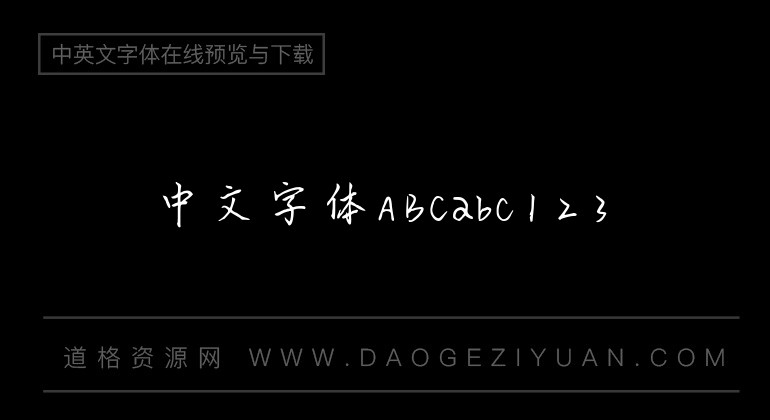
夏日玛奇朵
夏日玛奇朵字体是一种非常受欢迎的手写字体,其特点是线条柔和、圆润、自然流畅。它的灵感来自于夏日清晨,可以带给人们一种温暖、轻松、愉悦的感觉。 这种字体由小写和大写字母、数字、标点符号和特殊字符组成,可以应用于各种场合,如海报设计、卡片制作、个人博客和社交媒体等。使用夏日玛奇朵字体可以帮助传达出一种轻松自然的氛围,让人感觉仿佛置身于海滩、花园或森林之中。 总的来说,夏日玛奇朵字体是一种非常时尚、流行、适用广泛的字体,可以给人们带来愉悦、舒适、自然的感觉,是设计师和爱好者们喜爱的选择。
夏日玛奇朵是一款非常不错的手写艺术字体,具有很好的视觉感,适合于文化类的宣传设计、商业类品牌的广告和产品包装设计以及个性化文字排版等较多场景。